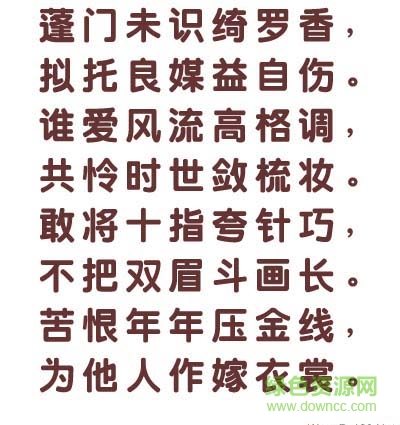
yentieg ultra gb(文鼎特粗圓簡)字體是一款邊角圓潤的文鼎字體,這款字體構(gòu)思精巧,柔軟流暢,溫和無鋒芒眼,不論是用作廣告字體還是文章排版字體都不錯!
1.無襯線字體用于小篇幅的宣傳品,圖注,摘要或者其他一些地方是比較好的;
2.長篇大論或者文學化的東西還是使用襯線比較好。因為與襯線字體相對應(yīng)的聯(lián)想是長篇大論或者小說,而與無襯線相關(guān)聯(lián)的聯(lián)想是比較圖形化的聯(lián)想(或者說無襯線更好的能與圖片相適應(yīng))。
3.凡是圖文并茂的文件都應(yīng)該考慮部分或者全部使用無襯線,而純文本要優(yōu)先考慮襯線。另個原因是無襯線比較容易無聊,多一些圖片可以調(diào)劑一下。
4.至于說標題,大膽的來無襯線吧!在醒目程度與設(shè)計感上面,無襯線的高度是襯線遠遠無法達到的。